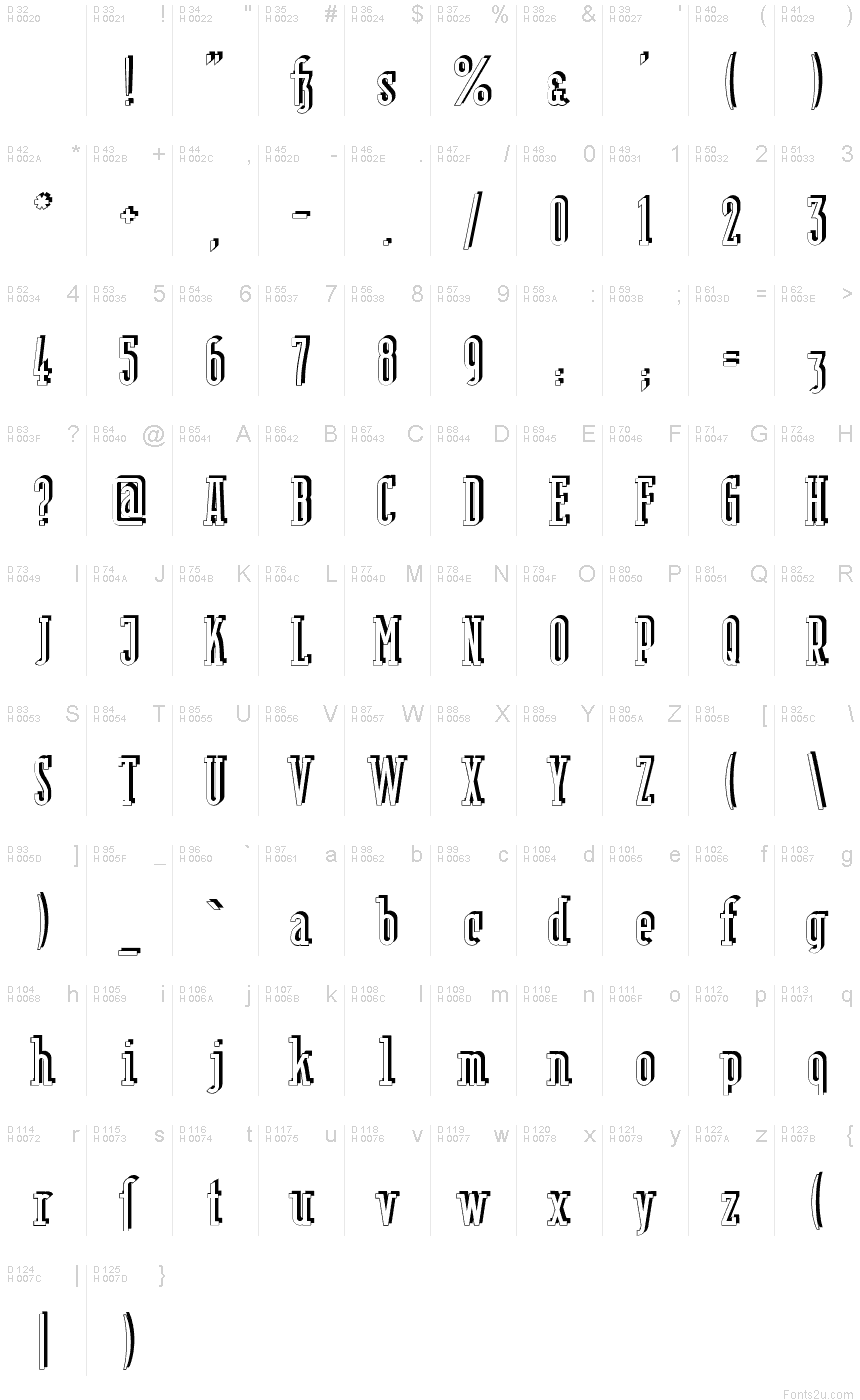
Berlin Email Serif Shadow von Peter Wiegel ist eine kostenlose Retro-Schrift mit Serifen, Schatten und Display-Charakter, die an alte Plakate erinnert. Die Buchstaben kombinieren kräftige Serifenformen mit einem präzisen versetzten Schatten und einer feinen Kontur. So erhält die Schrift diesen geschichteten Look der Plakatmalerei des frühen 20. Jahrhunderts, ohne dabei ihren direkten, handwerklichen Charakter zu verlieren.
Sie eignet sich hervorragend für Vintage-Branding, Café-Menüs, Buchcover, Veranstaltungsposter und Verpackungen, bei denen Schlagzeilen diesen typischen „Druck“-Look benötigen. Als kostenlose Schrift passt sie zudem perfekt für Titelkarten, Kopfzeilen und kurze Zitate, da die Schattenwirkung selbst wenigen Wörtern genug Präsenz verleiht, um die Seite zu tragen.
Berlin Email Serif Shadow